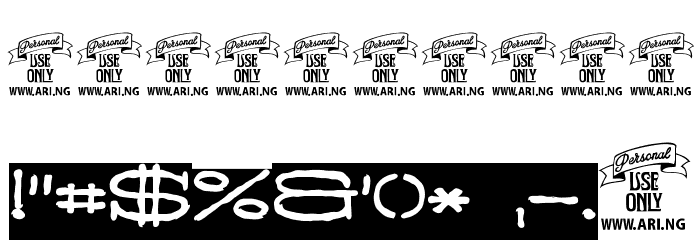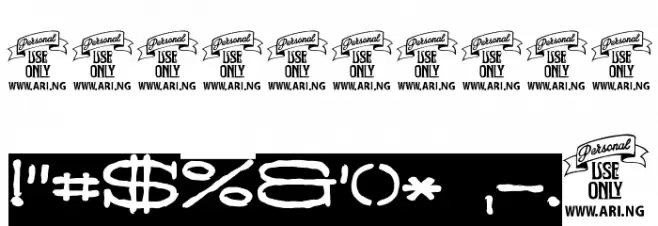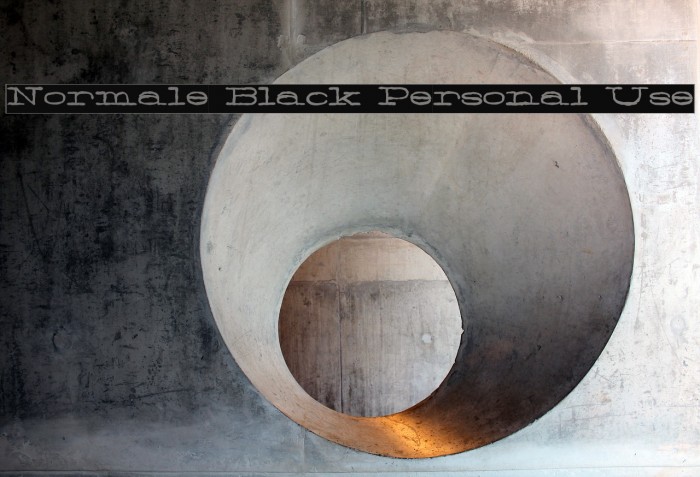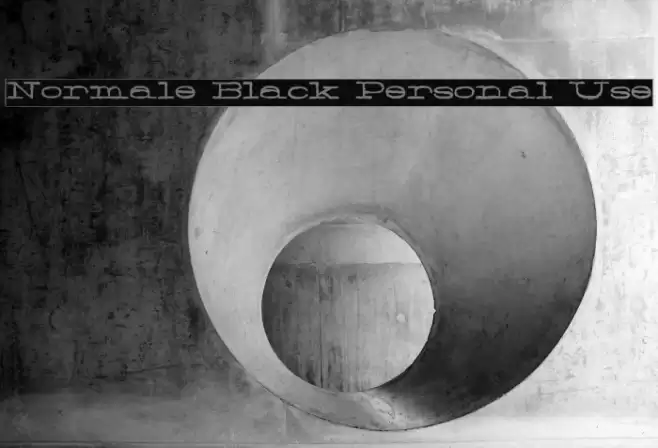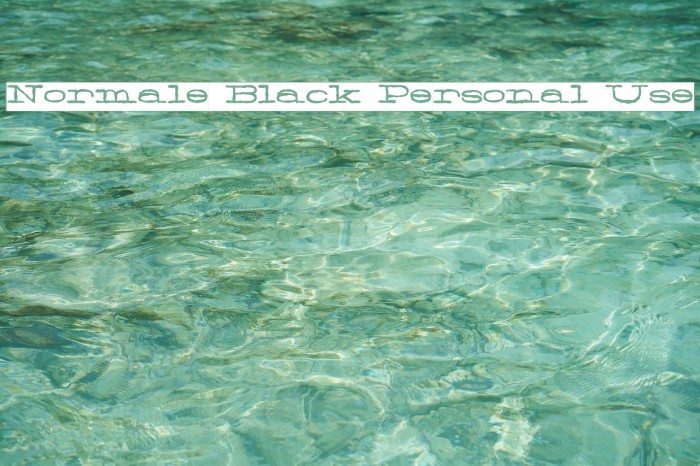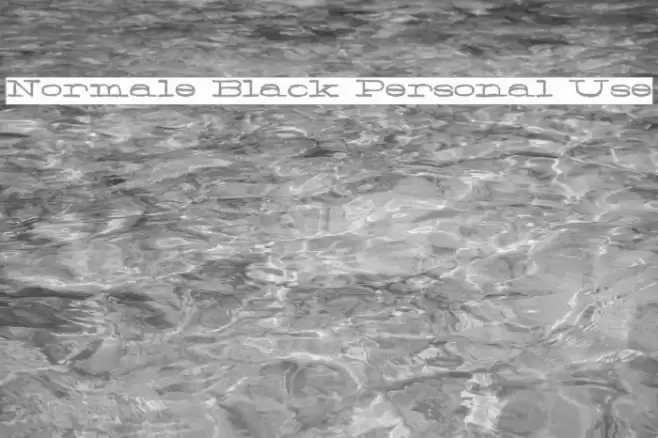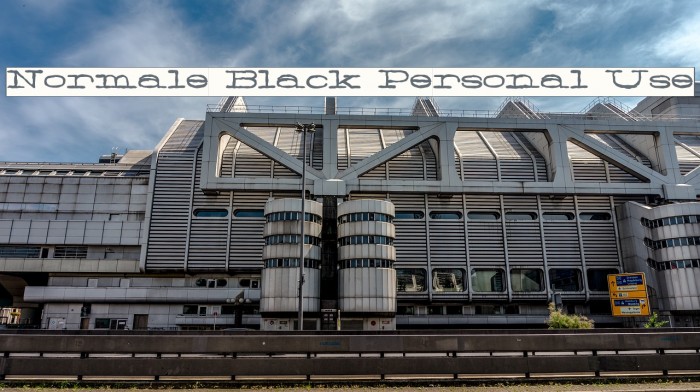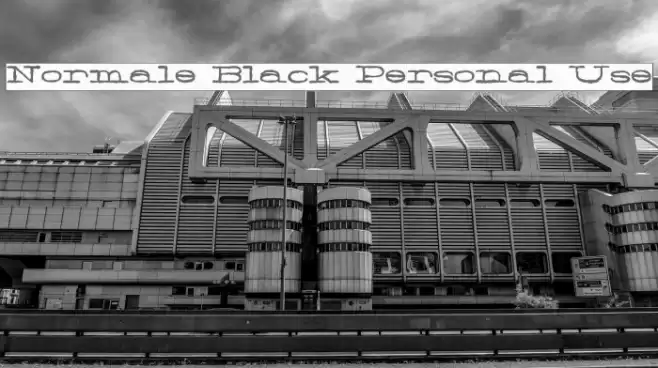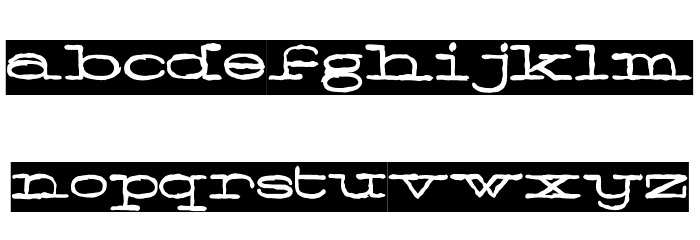
Normale Black Personal Use Font
✎ Typewriter
| Projetos propostos | Ideal for projects that require a vintage or retro feel, such as posters, album covers, or branding for artisanal products. |